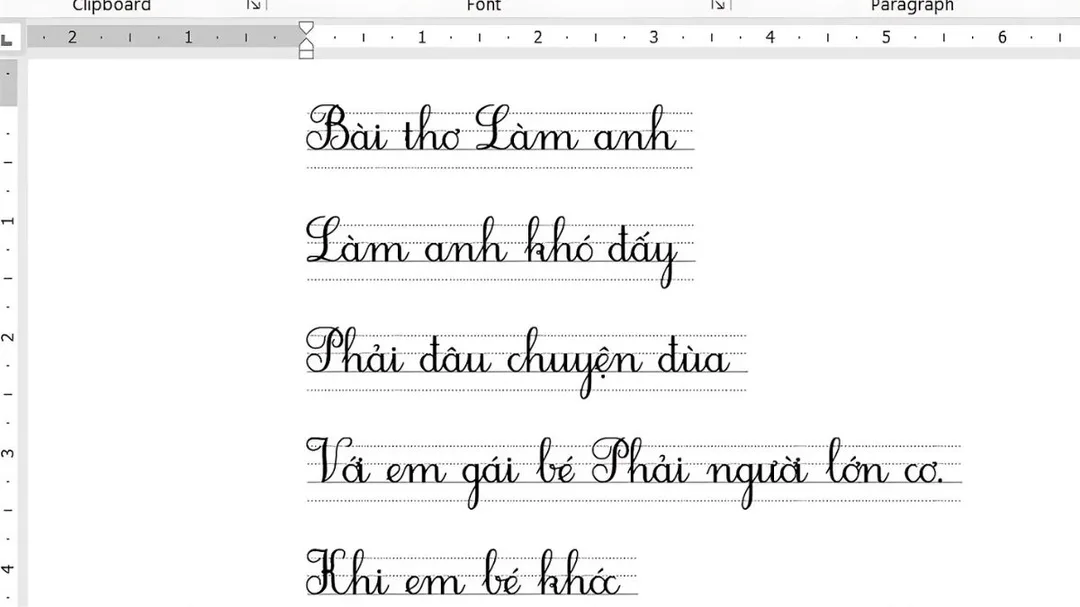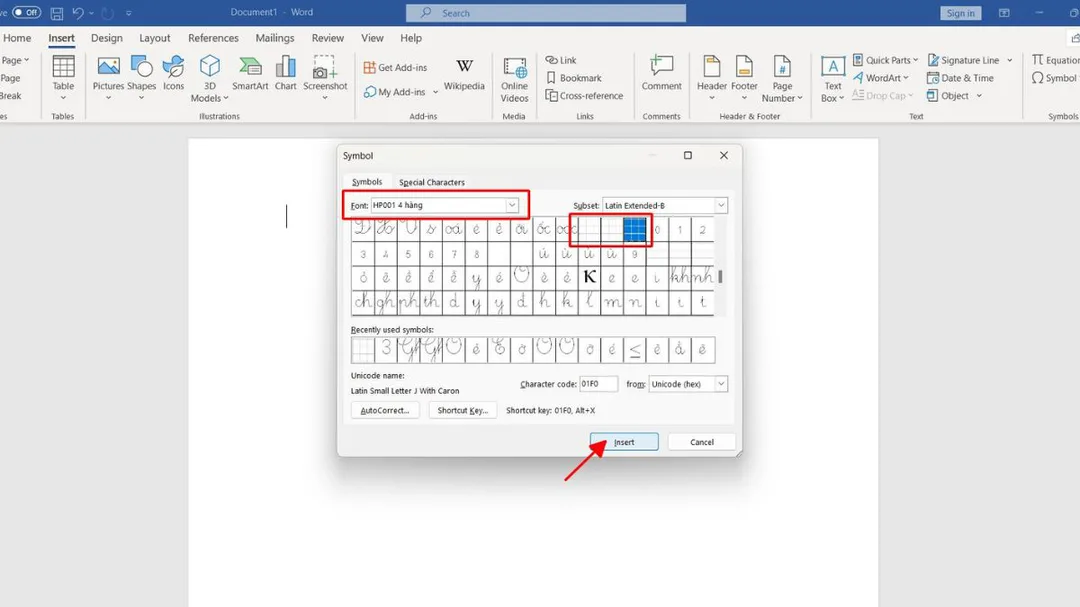
Cách cài font chữ tiểu học vào máy tính giúp giáo viên và phụ huynh soạn bài tập luyện chữ cho học sinh cấp 1. Font chữ tiểu học được thiết kế theo chuẩn Bộ Giáo dục, có nét chữ cân đối và phù hợp vở ô ly. Hướng dẫn dưới đây bao gồm cách tải, cài đặt, cấu hình Unikey và sử dụng font trong Microsoft Word.
Ưu điểm khi sử dụng font chữ tiểu học
Font chữ tiểu học được thiết kế riêng cho việc dạy viết cấp 1, mang lại nhiều lợi ích thiết thực cho cả giáo viên và học sinh.
Font chữ tiểu học giúp rèn luyện chữ viết
Font chữ tiểu học giúp rèn luyện chữ viết hiệu quả
Cấu trúc chuẩn theo Bộ Giáo dục: Nét chữ đảm bảo tỉ lệ cân đối giữa các nét sổ, nét móc, nét cong. Học sinh hình thành thói quen viết đúng ngay từ năm lớp 1.
Tương thích với vở ô ly: Kích thước font phù hợp với dòng kẻ ô ly tiêu chuẩn. Giáo viên có thể in bài tập trực tiếp từ Word mà không cần chỉnh sửa khoảng cách dòng.
Hỗ trợ luyện viết: Font có điểm bắt đầu và kết thúc rõ ràng ở mỗi nét chữ. Một số font như HL Hoctro còn có nét đứt để học sinh tập tô theo.
Hình dáng thân thiện: Nét chữ mềm mại, bo tròn, đơn giản hóa — giúp học sinh dễ phân biệt và ghi nhớ mặt chữ.
Tạo hứng thú học tập: Kiểu font đẹp mắt, gần gũi với chữ viết tay thật khiến trẻ thích thú hơn khi luyện viết tại nhà.
Cách sử dụng font chữ tiểu học trong Word
Sau khi cài xong, mở Word để sử dụng.
Bước 1: Mở Microsoft Word → trong danh sách font, gõ tên font như HL Hoctro, HP001 4 hàng, HP001 5 hàng hoặc HP001 4 hàng 1 ô ly.
Chọn font tiểu học trong Word
Gõ tên font vào ô chọn font trong Word
Bước 2: Để tạo dòng kẻ ô ly, vào tab Insert → chọn SymbolMore Symbols.
Chèn biểu tượng ô ly
Insert → Symbol → More Symbols
Bước 3: Chọn font chữ tiểu học trong ô Font → tìm biểu tượng kẻ ô ly → nhấn Insert.
Tìm biểu tượng ô ly
Tìm và chèn biểu tượng ô ly từ font tiểu học
Bước 4: Nếu các dòng kẻ ô ly bị tách rời, vào Home → mở Paragraph Settings → chỉnh Line Spacing thành Exactly với giá trị phù hợp (thường 28-32pt).
Chỉnh Paragraph Settings
Chỉnh Paragraph Settings để ô ly liền mạch
Kết quả font chữ tiểu học
Kết quả: dòng kẻ ô ly hiển thị đúng chuẩn
Cấu hình Unikey để gõ tiếng Việt với font tiểu học
Sau khi cài font, cần đảm bảo Unikey cấu hình đúng để gõ tiếng Việt không bị lỗi dấu.
Bước 1: Mở Unikey từ khay hệ thống (icon chữ V hoặc E ở góc phải dưới). Nhấn chuột phải → chọn Bảng điều khiển (hoặc nhấn Ctrl + Shift + F5).
Bước 2: Trong cửa sổ Unikey, thiết lập:
• Bảng mã: chọn Unicode (không dùng VNI hoặc TCVN3)
• Kiểu gõ: chọn Telex hoặc VNI tùy thói quen
• Đảm bảo chế độ đang ở Vietnamese (biểu tượng V).
• Bước 3: Nhấn Đóng → mở Word và kiểm tra gõ thử. Nếu dấu tiếng Việt hiển thị đúng trên font tiểu học, cấu hình thành công.
⚠️ Lưu ý: Font tiểu học chỉ hoạt động với bảng mã Unicode. Nếu dùng bảng mã VNI hoặc TCVN3, chữ sẽ bị lỗi ký tự đặc biệt.
Các bộ font chữ tiểu học phổ biến
Dưới đây là 5 bộ font tiểu học được giáo viên sử dụng nhiều nhất.
Tên font Đặc điểm Phù hợp
HL Hoctro Chữ viết tay chuẩn, nét đứt để tập tô, dễ đọc Lớp 1, tập tô chữ cái
HP001 4 hàng Kẻ 4 dòng chuẩn vở ô ly, nét liền Lớp 1-2, luyện viết chữ
HP001 5 hàng Kẻ 5 dòng chi tiết, hỗ trợ nét sổ Lớp 1, tập nét cơ bản
HP001 4 hàng 1 ô ly 4 dòng + 1 cột ô ly phía trước In mẫu bài tập, đề kiểm tra
HL Hoctro là font phổ biến nhất — phù hợp lớp 1 vì có nét đứt giúp trẻ tô theo.